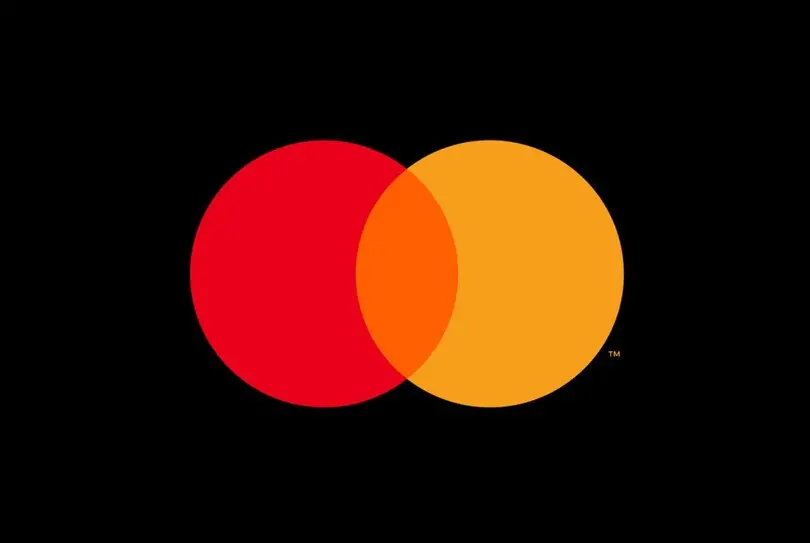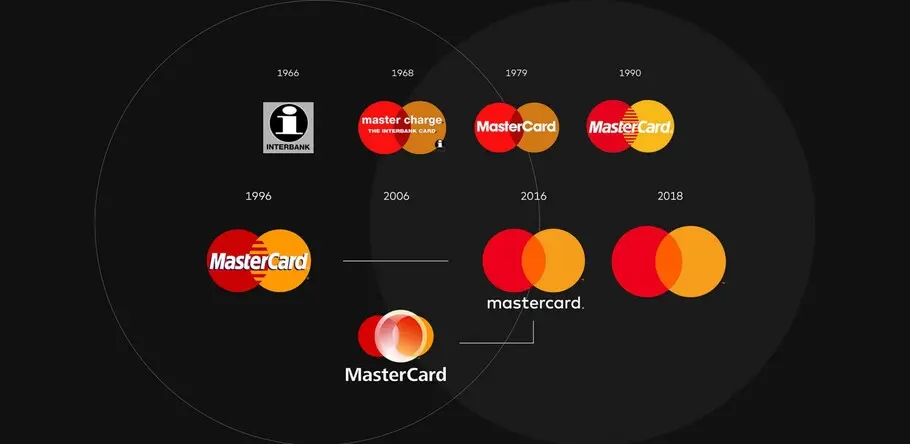
マスターカードのロゴが現代のブランドについて教えてくれること
「 マスターカードは、シンボルと色だけで80%の認識成功率のあるブランドに成長しました 」
Mastercard’s logo tells us about the modern brand.
マスターカードはリブランディングの際に、ロゴから「Mastercard」という言葉を省くこと発表し、話題を呼びました。しかし、この決定は、ブランドが自らを表現する方法においてより広範なトレンドの兆候なのか、それとも単にマスターカードが変化する市場に対処しているだけなのか、どちらなのでしょうか?
ワードマークを持たないロゴとは
ワードレスなロゴを採用するブランドはマスターカードだけではありません。 例えば、Apple、McDonald’s、Starbucks、Nikeなどです。企業がビジネスと顧客関係の急速なデジタル化に適応する中で、私たちはデジタルエクスペリエンスに焦点を当てたリブランディングに方向性をシフトしていく企業をいくつも見てきました。Mastercardの具体的なケースでは、そのデジタル化の中に、名前のルーツである物理的なクレジットカードが存在しない未来も含まれています。それは、オンラインでの購入がますます増加し、物理的なショップではキャッシュレス決済を好む時代にマッチした、財布やプラスチックのカードを持たないという未来です。
新しいロゴは、シンプルな形状と色(そして何十年もの馴染み深さ)のみで顧客とのつながりを築いています。
ワードレスなロゴを採用するということは、デジタルスクリーンなどのすべての環境でブランドを効果的に伝えることがより重要な課題となります。また、広告スペースが限られており、これらの環境で言葉の可読性を確保するのは難しい場合もあります。
企業がブランディングを簡素化する方法を探る中で、他の企業もマスターカードの道をたどることになるのでしょうか?そして、それはすべてのブランドにとって正しい決定なのでしょうか?
リブランドのタイミング
マスターカードはこの決定に一晩でたどり着いたわけではありませんでした。50年の歳月を経て一般の意識に根付いた普遍的なブランドに成長し、2016年のリブランドでは、ワードマークと赤と黄色の組み合わさった円環を分離することで基盤を築きました。
2016年のマスターカードのリブランドを主導した担当者は「これらの要素を分離した大規模なデザインを行った際、シンボルを単独で使用できる状況を想定しました。特にデジタルの世界では、ロゴがますます小さく表示されるため、10文字のMastercardの名前なしで使用できるようにすることは、好機であり同時に必要なことのように思われました。」と述べています。また、このリブランドでは、FF MarkというMonotypeのフォントが採用され、現在も使用され続けています。
マスターカードはシンボルとカラーだけで80%の認識成功率を挙げていますが、それには数十年かかりました。マクドナルドの場合は、創業者たちは当初からそのアーチをレストランで使用しており、それが浸透し十分にブランドが確立した上でワードレスなロゴを採用しました。Nikeも同様に、スウッシュのみのロゴを確立するのに25年の道のりを歩みました。
多くの面で、ワードマークを省くことはステータスシンボルであり、ブランドが世界的にも認知されていることを主張する手段の一つです。マスターカードは新しいロゴを発表する中で「私たちの伝統ある豊かなブランドに誇りを持ち、独立したアイコニックな円で構成されたロゴを発表することができて大変喜ばしく思っています。」と述べています。
しかし、マスターカードやマクドナルドのような既存のブランドがその認識を築くのに何世代もかかった一方で、デジタル時代に生まれ育ったブランドはわずか数年で同じレベルの知名度を獲得している例も存在します。
FacebookやTwitter(現在はX)のシンボルとアイコンは急速に浸透していきました。他のデジタル企業、例えばAirBnBなども、単語よりもモバイルファーストのライフスタイルに特化した独自かつシンプルなロゴに依存するアイデンティティシステムに素早く移行しました。
物理的なカードをはじめとする多くのタッチポイントからワードマークがないロゴにアップデートされていきます。
ワードレスな未来について
Interbrand 100を見ると、実はまだワードマークを持たないロゴを採用する企業は、上位100のうちたったの7つですが、今後もMastercardのようなブランドに続く企業が増えるでしょう。未来に対応したブランドを作るためには、ワードレスなシンプルさを実現することが重要になってくるからです。